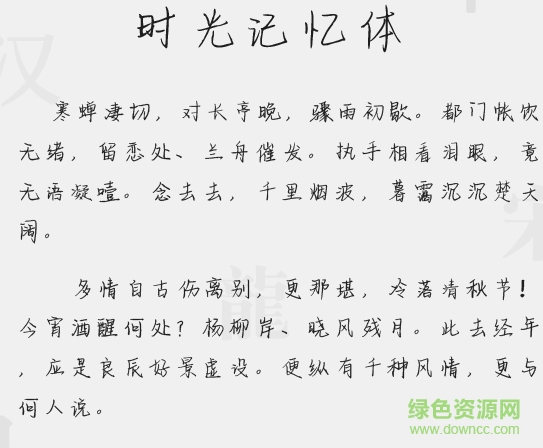
時光記憶.ttf是小米手機(jī)推出的一款藝術(shù)字體,字跡清秀婉約,柔和的筆觸讓你感受時光如水的靜靜流淌,造型干凈充滿靜好氣息,喜歡的朋友來綠色資源網(wǎng)下載體驗(yàn)吧!
時光記憶體是鋼筆書法字體,字跡清晰隨意,適合平面設(shè)計(jì)、廣告設(shè)計(jì)、海報(bào)設(shè)計(jì)等多種領(lǐng)域,讓你的文字具有不一樣的美感和視覺享受!